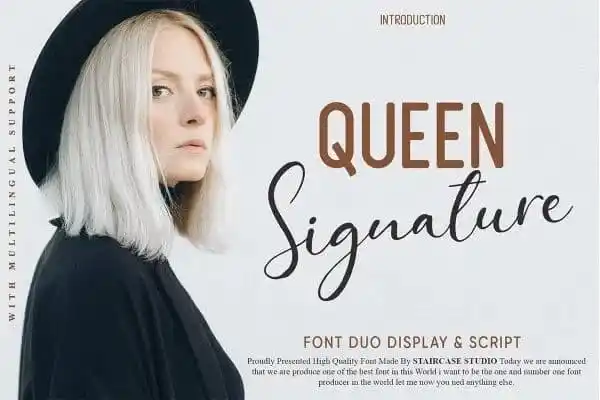
Queen Signature Font Duo – Download Grátis
A ‘Queen Signature Font Duo’ é uma maravilhosa dupla de fótons que combina uma elegante escrita assinatura com traços serifados modernos e uma fluidez natural e sofisticada. Desenvolvida pela 99designs, essa fonte perfeita para a identificação pessoal se destaca por sua proporção clássica e estilo suave, adequada para criar marcas de alta qualidade que destacam sua personalidade única. Seja você um designer, uma marca ou até mesmo alguém que busca dar um toque especial à sua escrita diária, essa fonte oferece a oportunidade de expressar-se de maneira diferenciada e sofisticada. É uma escolha perfeita para aqueles buscando personalizar seus materiais com estilo próprio.